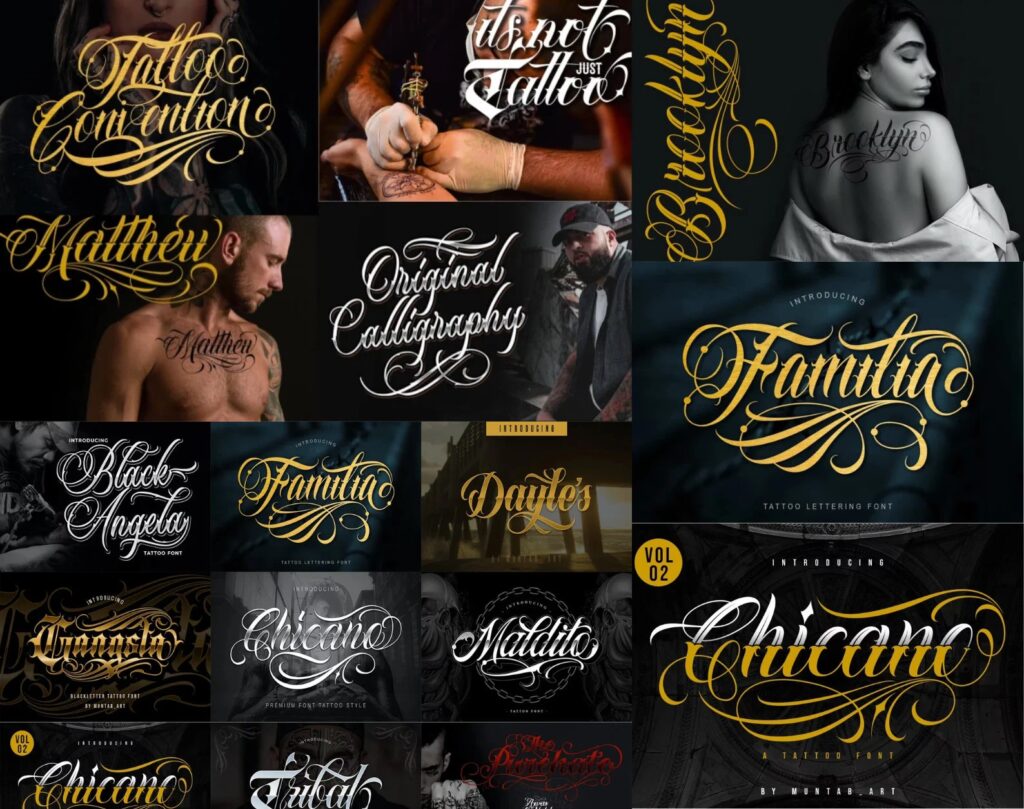
At vælge en tatovering er en dybt personlig beslutning, og når tatoveringen indeholder tekst eller bogstaver, bliver valget af skrifttype lige så vigtigt som selve ordene. Skrifttypen sætter tonen, formidler følelser og sikrer, at budskabet er tydeligt og æstetisk tiltalende i mange år fremover. Uanset om du overvejer et enkelt ord, en meningsfuld sætning som "Temet Nosce" eller et helt citat, er skrifttypen afgørende for det endelige udtryk.
Mange står over for spørgsmålet: Skal man vælge noget klassisk og tidløst, som for eksempel romerske kapitæler inspireret af gamle monumenter? Eller passer en mere moderne, blokagtig eller måske endda en elegant skråskrift bedre? Der er et utal af muligheder, og hver stilart har sine egne kendetegn og overvejelser.
Hvorfor Skrifttypevalget Er Vigtigt
Skrifttypen er ikke bare en måde at formidle ordene på; den er en integreret del af tatoveringens design. En forkert skrifttype kan gøre teksten svær at læse, forringe det visuelle udtryk eller endda få tatoveringen til at ældes dårligt. Faktorer som størrelse, placering på kroppen og detaljeringsgrad spiller alle ind, når du skal vælge den rette skrifttype. En skrifttype, der ser fantastisk ud i stor størrelse på et fladt område, fungerer måske ikke i en mindre størrelse på et kurvet område af kroppen, hvor linjerne kan flyde sammen over tid.
Klassiske vs. Moderne Skrifttyper
Når man tænker på teksttatoveringer, dukker der ofte to hovedkategorier op: klassiske og moderne skrifttyper.
Klassiske Skrifttyper
Klassiske skrifttyper trækker ofte på historiske fonte, som dem der findes i gamle manuskripter, på monumenter eller i traditionel typografi. Eksempler inkluderer:
- Romerske Kapitæler: Inspireret af inskriptioner fra antikkens Rom, som dem på Trajansøjlen. Disse er ofte store, blokagtige bogstaver uden små fødder (seriffer), der udstråler styrke, autoritet og tidløshed. De er meget læselige, især i større størrelser.
- Gotisk Skrift (Blackletter): Denne stilart, også kendt som Blackletter eller Fraktur, er karakteriseret ved sine dramatiske, tunge strøg og udsmykkede detaljer. Den har historiske rødder i middelalderen og bruges ofte til at give et old-school, dramatisk eller mystisk udtryk. Gotisk skrift kræver ofte mere plads og detaljer for at bevare læsbarheden.
- Skråskrift (Script): Selvom mange skråskrifter er moderne, findes der også klassiske varianter, der efterligner elegant håndskrift eller kalligrafi. Disse kan variere fra enkle, flydende linjer til meget udsmykkede, dekorative stilarter. Skråskrift kan give et personligt, elegant eller romantisk præg.
Valget mellem disse klassiske stilarter afhænger meget af den ønskede æstetik og budskabet. Romerske kapitæler passer godt til korte, slagkraftige sætninger, mens gotisk skrift er ideel til noget, der skal se gammelt eller dramatisk ud. Skråskrift er perfekt til navne, datoer eller citater, der skal føles flydende og personlige.
Moderne Skrifttyper
Moderne skrifttyper dækker et bredt spektrum og er ofte mere minimalistiske, eksperimenterende eller inspireret af nyere design trends:
- Sans-serif Skrifttyper: Bogstaver uden de små fødder (seriffer). Disse er ofte meget rene, minimalistiske og lette at læse. De giver et moderne, rent og strømlinet look.
- Blokskrifttyper: Tunge, ofte firkantede bogstaver, der kan have et industrielt, grafisk eller tegneserieagtigt udtryk. De er gode til at skabe visuel vægt og kan fungere godt i større designs.
- Minimalistiske Skrifttyper: Meget enkle, ofte tynde linjer, der passer perfekt til minimalistiske tatoveringsdesigns. De fokuserer på form og negativt rum.
- Grafiske Skrifttyper: Skrifttyper der bryder med traditionelle former og inkorporerer grafiske elementer, teksturer eller utraditionelle streger.
Moderne skrifttyper giver stor fleksibilitet og mulighed for at skabe et unikt, nutidigt design. De passer godt til en bred vifte af temaer, fra abstrakte koncepter til popkulturelle referencer.
Populære Tatoveringsstile og Tekst
Teksttatoveringer falder ofte ind under eller komplementerer flere forskellige tatoveringsstile. Forståelsen af disse stilarter kan hjælpe med at vælge den rette skrifttype og det overordnede design.
- Lettering (Script Tattoos): Dette er en stilart dedikeret udelukkende til tekst. Den omfatter alt fra elegant kalligrafi og skråskrift til dristige, blokagtige fonte og gotiske stilarter. Inden for Lettering er skrifttypevalget og kompositionen altafgørende. Populære valg inkluderer:
- Cursive: Til et delikat, flydende look.
- Gothic: Til et dramatisk og historisk udtryk.
- Bold Lettering: Til et stærkt, slagkraftigt statement.
Lettering tattoos er ofte valgt for deres personlige betydning og bruges til at mindes begivenheder, udtrykke overbevisninger eller ære kære.
- Minimalistiske Tatoveringer: Kendetegnet ved enkle, nedtonede designs, rene linjer og minimal skygge eller detaljer. Tekst i minimalistiske tatoveringer bruger ofte tynde, rene sans-serif fonte eller enkle skråskrifter. Fokus er på klarhed og subtilitet. Små symboler, linjer og kort tekst er populære i denne stil.
- Fine Line Tattoos: En underkategori af Line Art, der bruger meget tynde, præcise linjer. Tekst i Fine Line tatoveringer vil typisk bruge en delikat skrifttype, der matcher stilens elegance og detaljegrad. Læsbarhed i meget små størrelser kan være en udfordring over tid på grund af blækspredning.
- Blackwork Tatoveringer: Anvender udelukkende sort blæk, ofte med solide sorte områder og dristige linjer. Tekst i Blackwork kan variere fra gotisk skrift integreret i et større mønster til dristige, blokagtige bogstaver, der bruger negativt rum. Stilen er kendt for sin stærke visuelle effekt.
- Trash Polka: En unik stilart, der kombinerer realisme, grafiske elementer, kalligrafi, skrivemaskinetekst og abstrakte former, ofte i sort og rød blæk. Tekst i Trash Polka er ofte kaotisk, grafisk og integreret med andre elementer som blækstænk og collage-lignende kompositioner. Skrifttypen kan være meget varieret, fra realistisk skrivemaskinetekst til håndskrevne noter.
- Illustrative Tatoveringer: Disse tatoveringer ligner tegninger eller skitser. Tekst kan indarbejdes som en del af illustrationen, måske i en håndskrevet stil, der passer til det illustrative udtryk, eller som et rent typografisk element, der komplementerer billedet.
- Tribal Tatoveringer: Traditionelt ikke en stilart, der fokuserer på tekst, men hvis tekst indarbejdes, vil det typisk være i dristige, blokagtige bogstaver, der matcher stilens tunge, sorte linjer og mønstre.
Valg af den Rette Skrifttype for Dig
Når du skal vælge skrifttype, er her nogle vigtige overvejelser:
- Budskabet: Hvilken følelse eller stemning skal teksten formidle? En alvorlig sætning passer måske bedst med en klassisk, solid skrifttype, mens et legende citat kan bære en mere uformel eller moderne font.
- Placering: Hvor på kroppen skal tatoveringen sidde? Større, flade områder som ryggen eller låret giver mere plads til detaljerede eller udsmykkede skrifttyper. Mindre eller mere kurvede områder kræver ofte en simplere, mere læselig skrifttype.
- Størrelse: Hvor stor skal tatoveringen være? Meget små tekster med tynde linjer eller fine detaljer kan flyde sammen over tid. Større tekster giver mulighed for mere komplekse fonte.
- Læsbarhed: Er det vigtigt, at teksten er let at læse på afstand eller tæt på? Nogle meget dekorative skrifttyper kan være svære at afkode.
- Ældning: Hvordan vil skrifttypen se ud om 5, 10 eller 20 år? Tynde linjer kan blive tykkere, og detaljer kan udviskes. En solidere skrifttype ældes ofte bedre.
- Kunstnerens Erfaring: Vælg en tatovør, der har erfaring med Lettering og den specifikke skrifttype, du ønsker. Nogle skrifttyper kræver en særlig teknik.
Værktøjer til at Finde Inspiration
Mange tatovører bruger digitale værktøjer og font-generatorer til at vise kunderne, hvordan forskellige tekster vil se ud i forskellige skrifttyper. Online font-databaser giver mulighed for at indtaste din tekst og se den visualiseret i tusindvis af forskellige fonte. Nogle platforme, som den nævnte Fotor, tilbyder endda specifikke tatoveringsfont-generatorer og designværktøjer, der lader dig eksperimentere med udseendet, før du besøger tatovøren.
Det er en god idé at bruge tid på at udforske forskellige fonte online. Skriv din tekst ind, prøv forskellige stilarter – romerske, gotiske, skråskrift, minimalistiske, blokagtige – og se, hvilke der visuelt appellerer mest til dig. Tag screenshots eller print dine favoritter med til din konsultation med tatovøren.
Overvejelser for Specifikke Tekster
For en tekst som "Temet Nosce", der består af to korte ord, er designmulighederne mange. Romerske kapitæler kunne give et klassisk, filosofisk udtryk, der passer til sætningens oprindelse. En moderne sans-serif kunne give et rent, nutidigt look. Gotisk skrift ville tilføje drama og vægt. Skråskrift kunne gøre det mere personligt og flydende. Overvej, hvilket udtryk du ønsker at give sætningen på din krop.
Ofte Stillede Spørgsmål om Tatoveringsskrifttyper
Q: Kan enhver skrifttype bruges til en tatovering?
A: I princippet ja, men ikke alle skrifttyper egner sig lige godt. Meget tynde, meget komplicerede eller meget små skrifttyper kan være svære at tatovere præcist og kan ældes dårligt, da blækket kan flyde sammen. En erfaren tatovør kan rådgive om, hvilke skrifttyper der er realistiske for din ønskede størrelse og placering.
Q: Hvad er forskellen på Gotisk skrift, Blackletter og Fraktur?
A: Gotisk skrift (Gothic script) er et bredt begreb for middelalderlige europæiske skrifttyper. Blackletter er det engelske udtryk for denne kategori. Fraktur er en specifik type Blackletter, der var udbredt i Tyskland. De er alle kendetegnet ved deres tunge, kantede former, men har varierende detaljer og udtryk.
Q: Hvordan påvirker placeringen skrifttypevalget?
A: Områder med meget bevægelse eller stræk (som led) eller områder, der udsættes meget for sol eller slid (som hænder og fødder), kan påvirke, hvordan en tatovering ældes. Dette kan have betydning for valget af skrifttype og detaljeringsgrad for at sikre, at teksten forbliver læselig.
Q: Hvad er den bedste skrifttype til et navn?
A: Skråskrift (Cursive) er et meget populært valg til navne på grund af sit personlige og flydende udtryk. Dog kan en simpel, ren sans-serif eller en klassisk blokskrifttype også fungere godt, afhængigt af den ønskede stil og læsbarhed.
Q: Skal jeg bruge en tatoveringsfont-generator?
A: En font-generator kan være et fantastisk værktøj til at visualisere din tekst i forskellige skrifttyper og få inspiration. Det erstatter dog ikke en konsultation med en professionel tatovør, der kan vurdere skrifttypens egnethed for tatovering og hjælpe med at finjustere designet.
Q: Hvilke skrifttyper ældes bedst?
A: Generelt ældes skrifttyper med klarere, tykkere linjer og færre fine detaljer bedre end meget tynde eller meget komplicerede fonte. Solbeskyttelse og god efterpleje er dog afgørende for, hvordan enhver tatovering holder sig over tid.
Afsluttende Tanker
Valget af skrifttype til din teksttatovering er en spændende del af processen. Det handler om at finde en balance mellem æstetik, læsbarhed og holdbarhed. Tag dig god tid til at udforske forskellige muligheder, brug eventuelt online værktøjer til at visualisere dine ideer, og vigtigst af alt: Tal med en erfaren tatovør. De kan give uvurderlig indsigt i, hvordan forskellige skrifttyper vil fungere på din hud og hjælpe dig med at træffe det bedste valg for din nye, meningsfulde